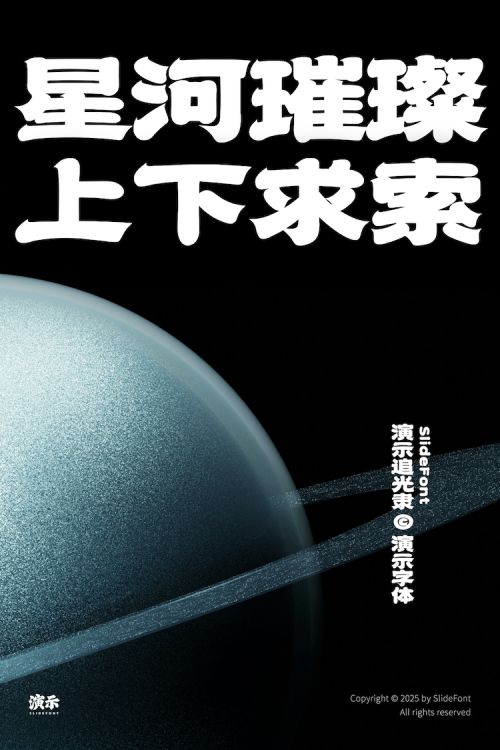
演示追光隶
其灵感源自清许容编、师古斋藏板的《许氏说篆》康熙十四年书牌大题,提取笔画特征并大胆创新。字体笔画刚柔并济,起笔收笔形态丰富多变,兼具隶书的古朴醇厚与灵动飘逸,书法韵味展露无遗。可广泛适用于古风海报、文化书籍封面、传统节日宣传物料、餐饮快消品等诸多场景,能够精准无误地传递国风韵味,既彰显典雅大气之风范,又洋溢着浓郁的烟火气息,为传统文化氛围的营造增添绚丽色彩。